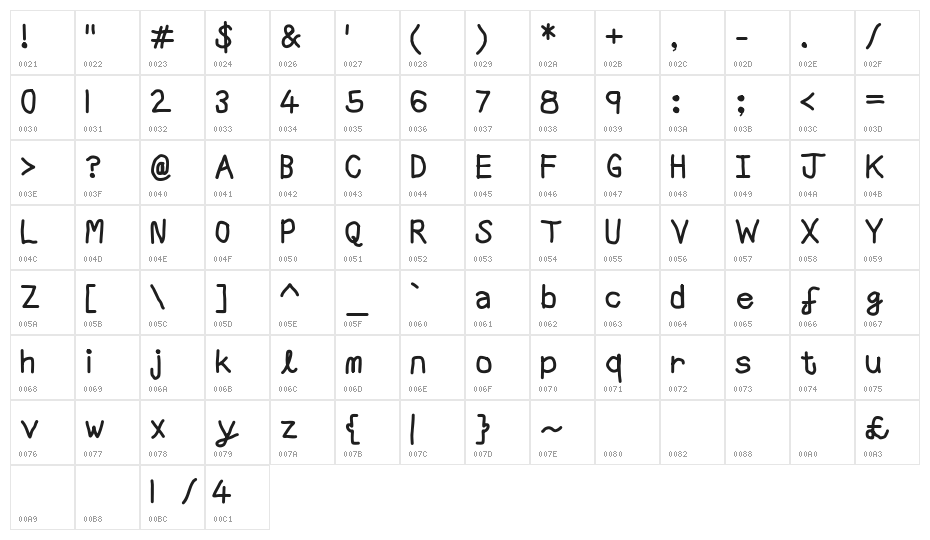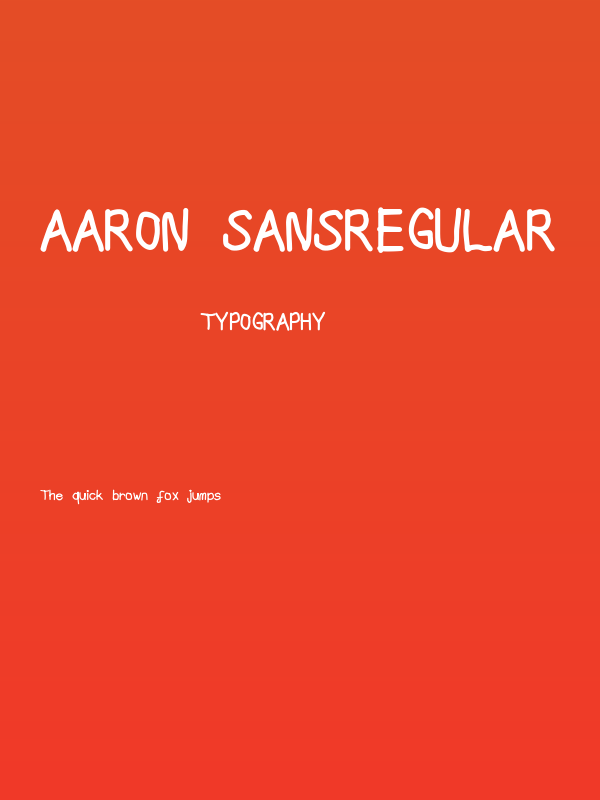
Aaron SansRegular Font
| Kategorien | Comic |
| Gesamtstil | Casual |
| Anwendungsfall | Headlines, Informal text, Branding |
| Vorgeschlagene Projekte | Ideal for greeting cards, invitations, children's books, and informal branding. |